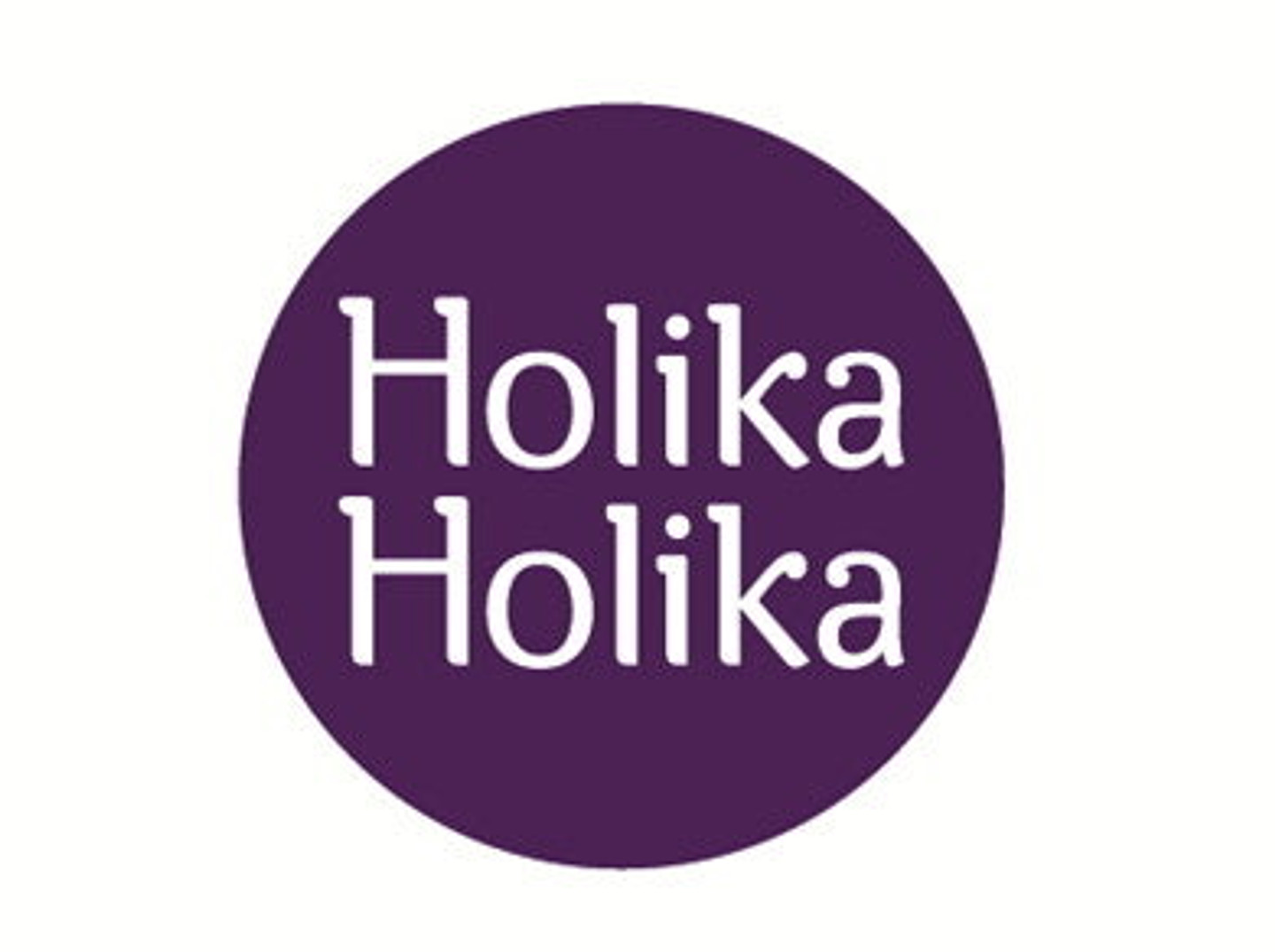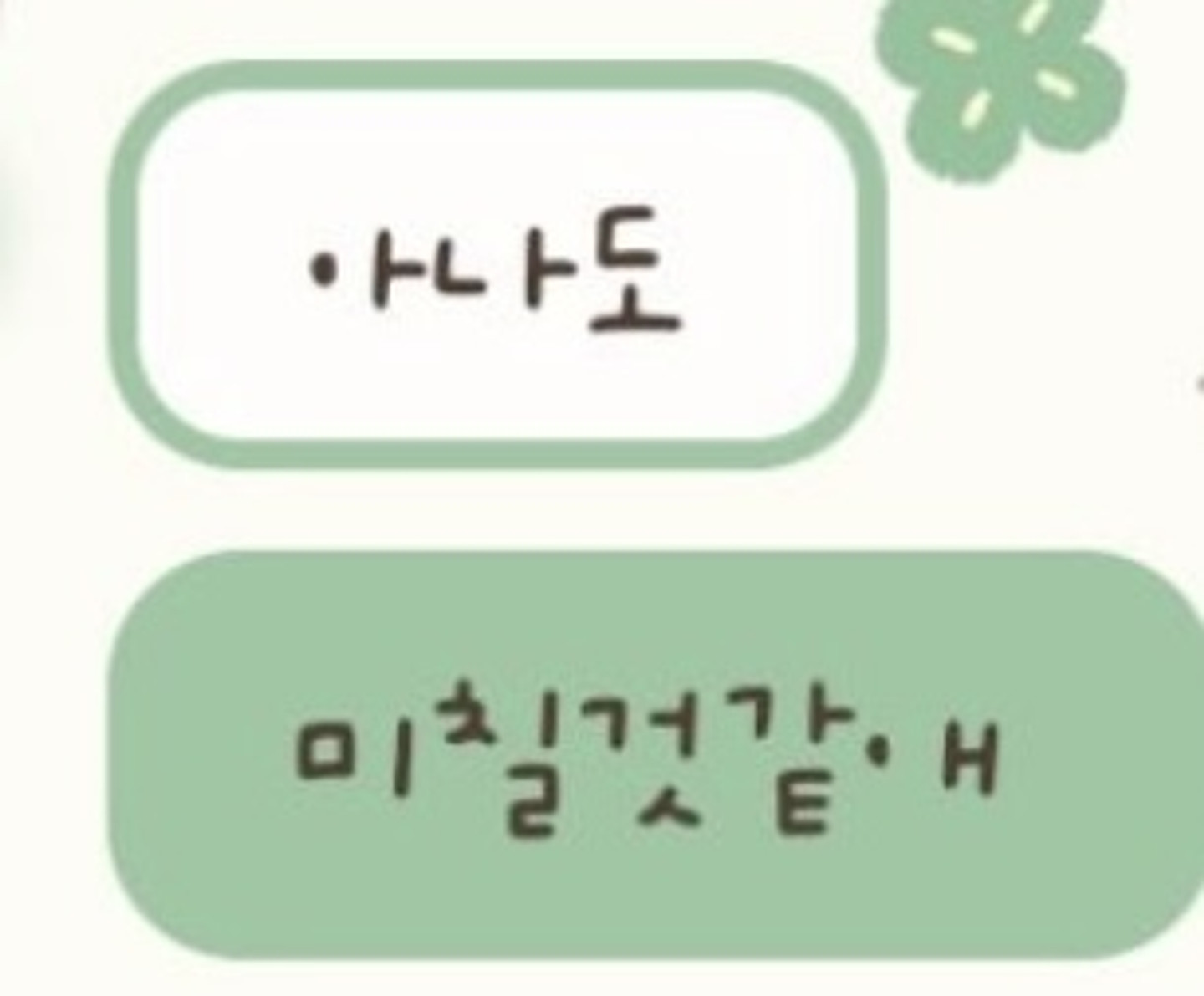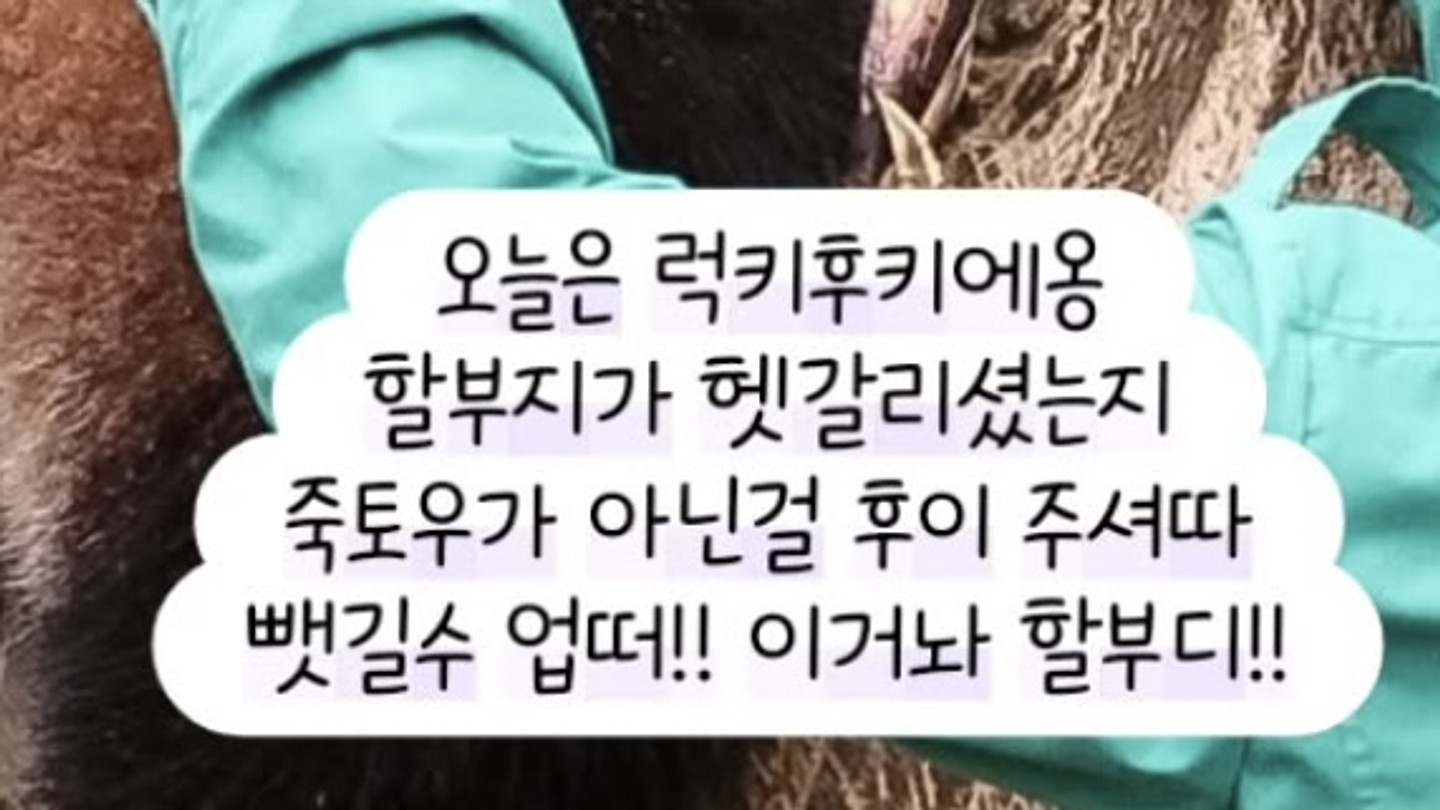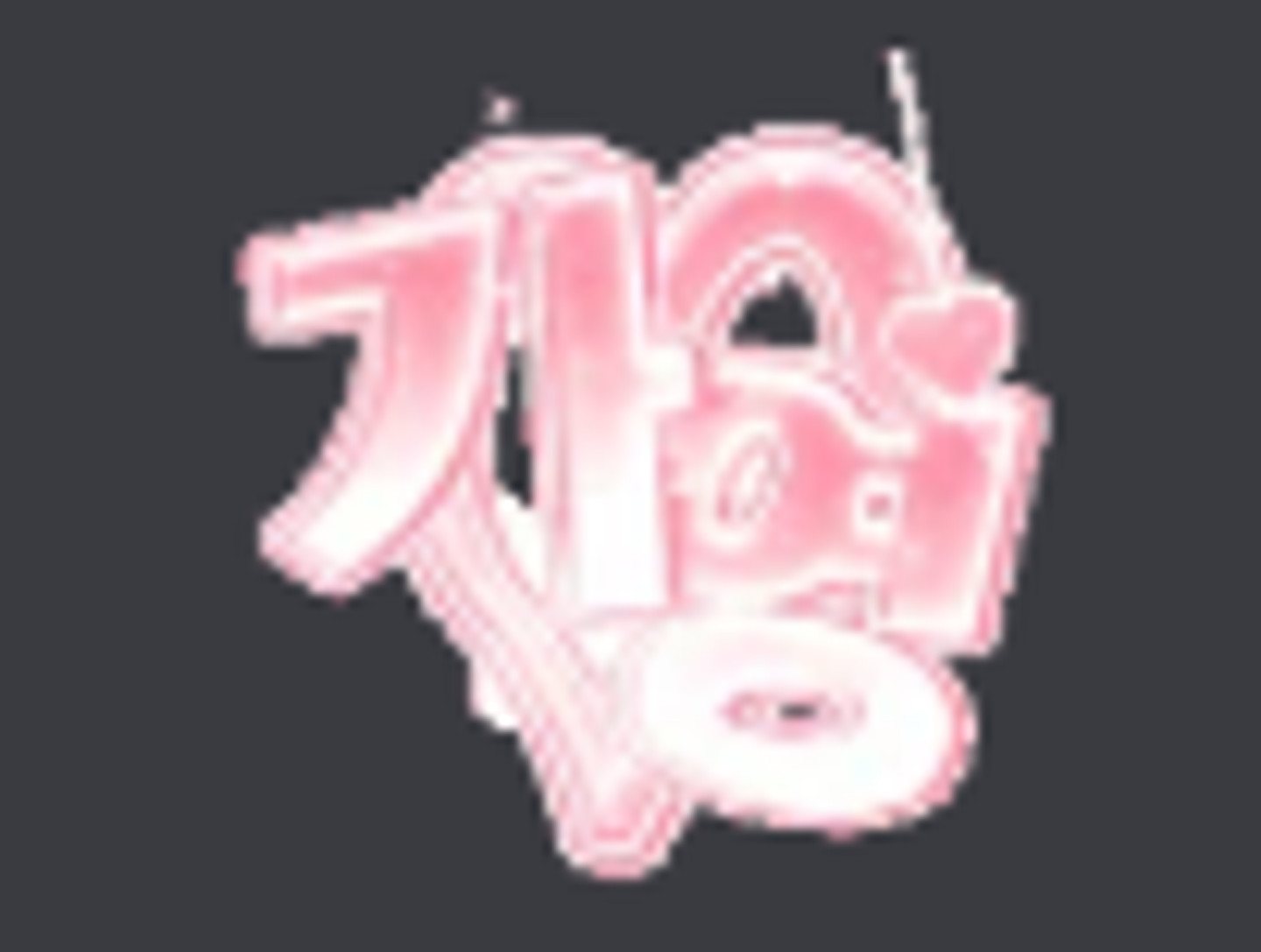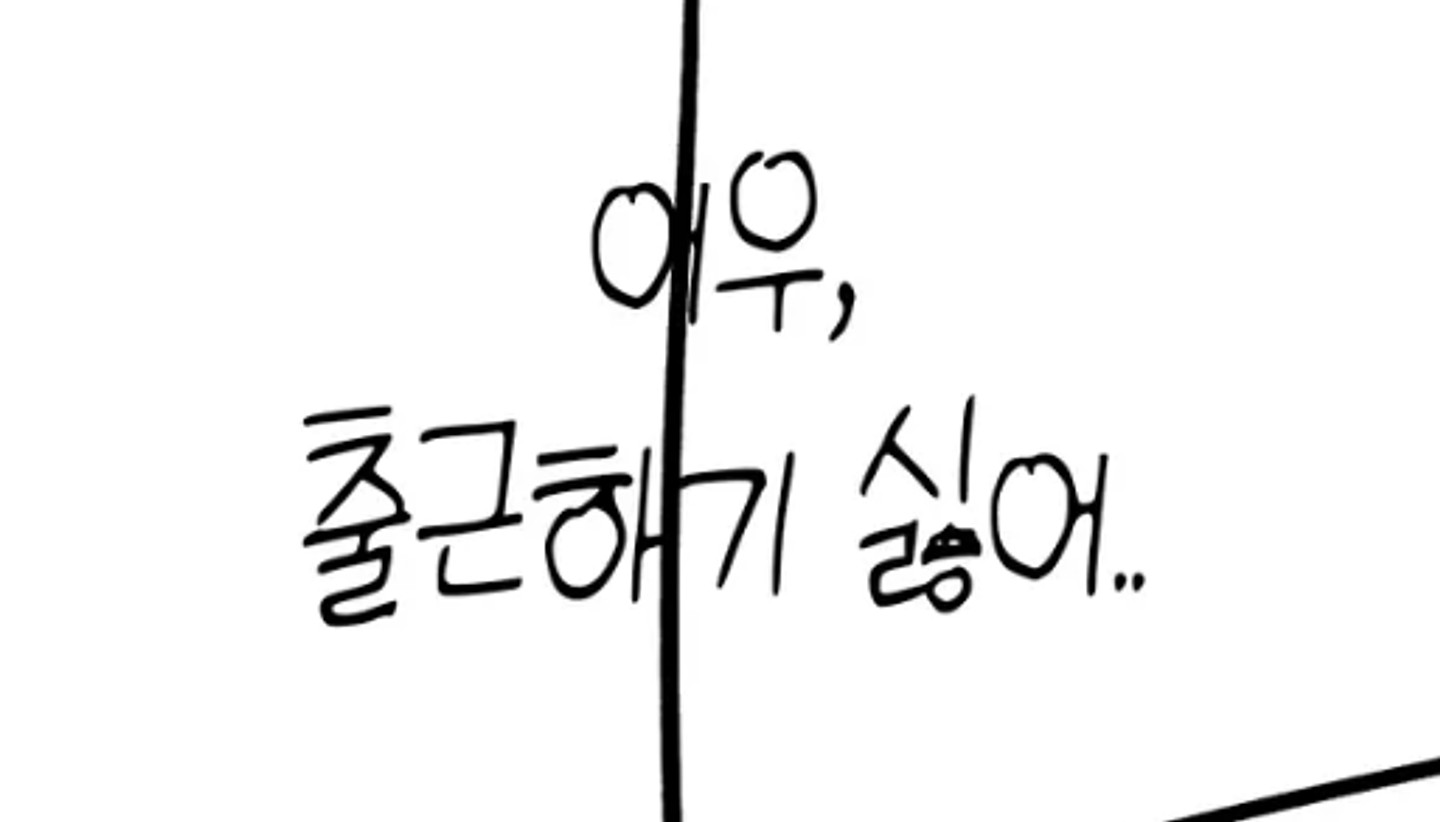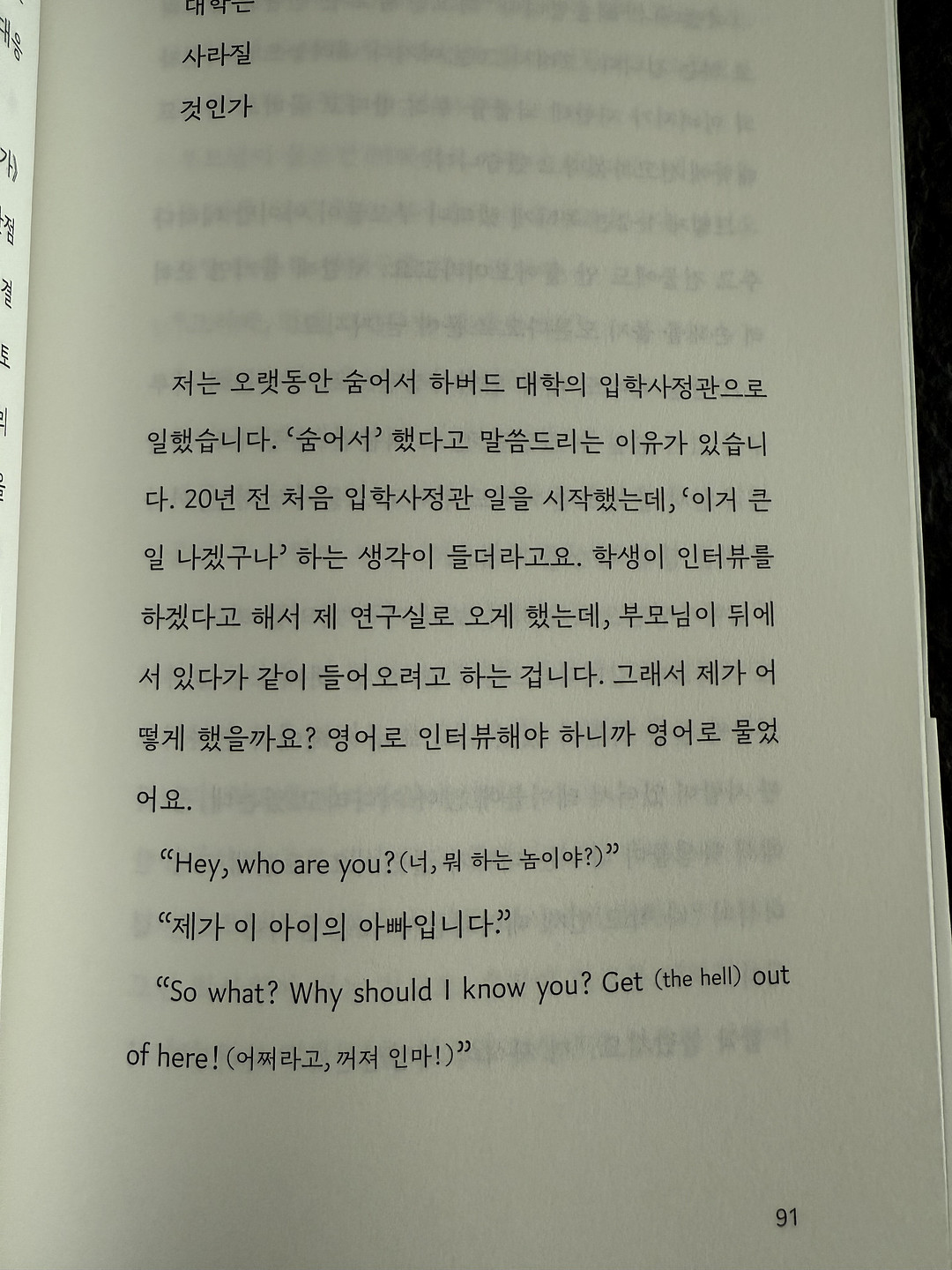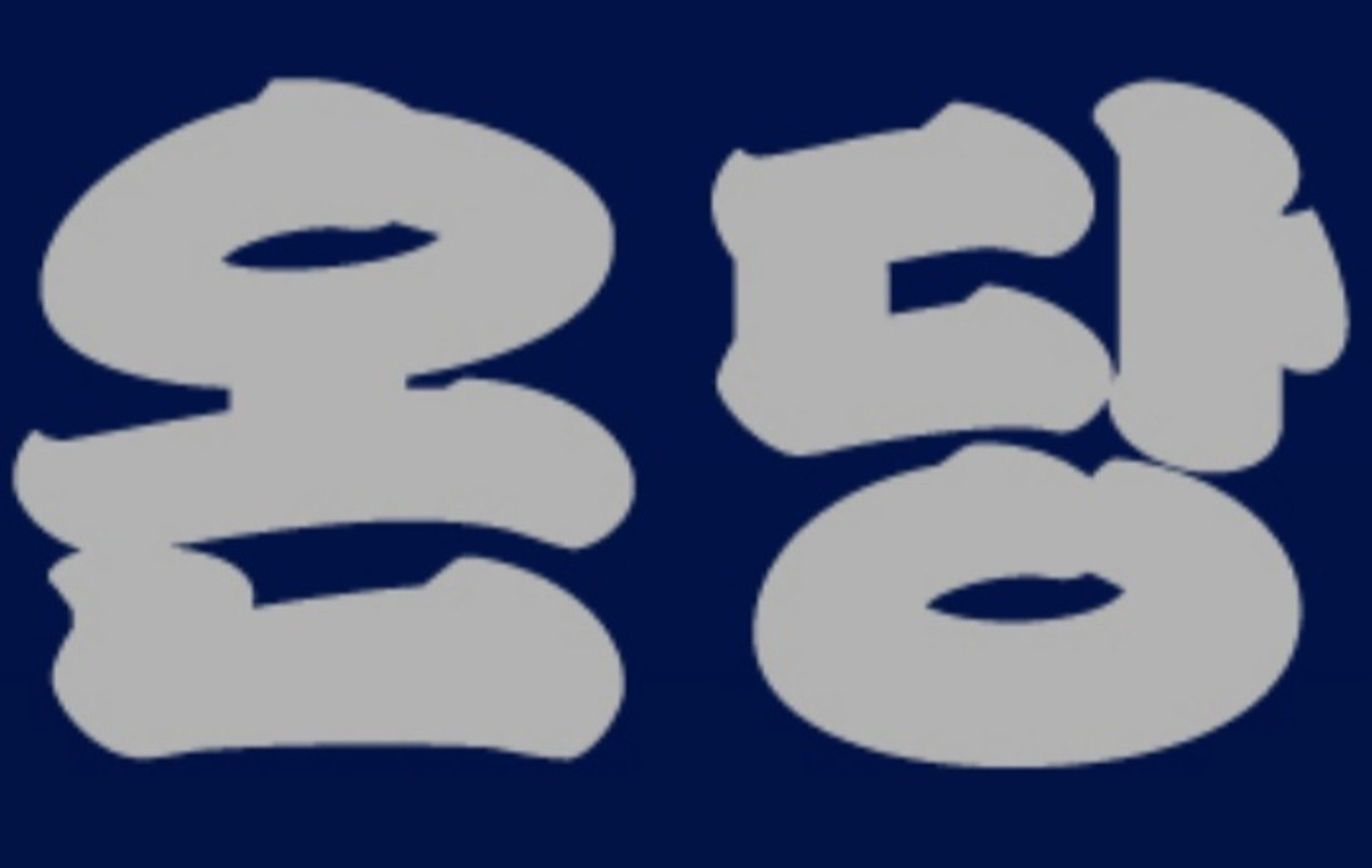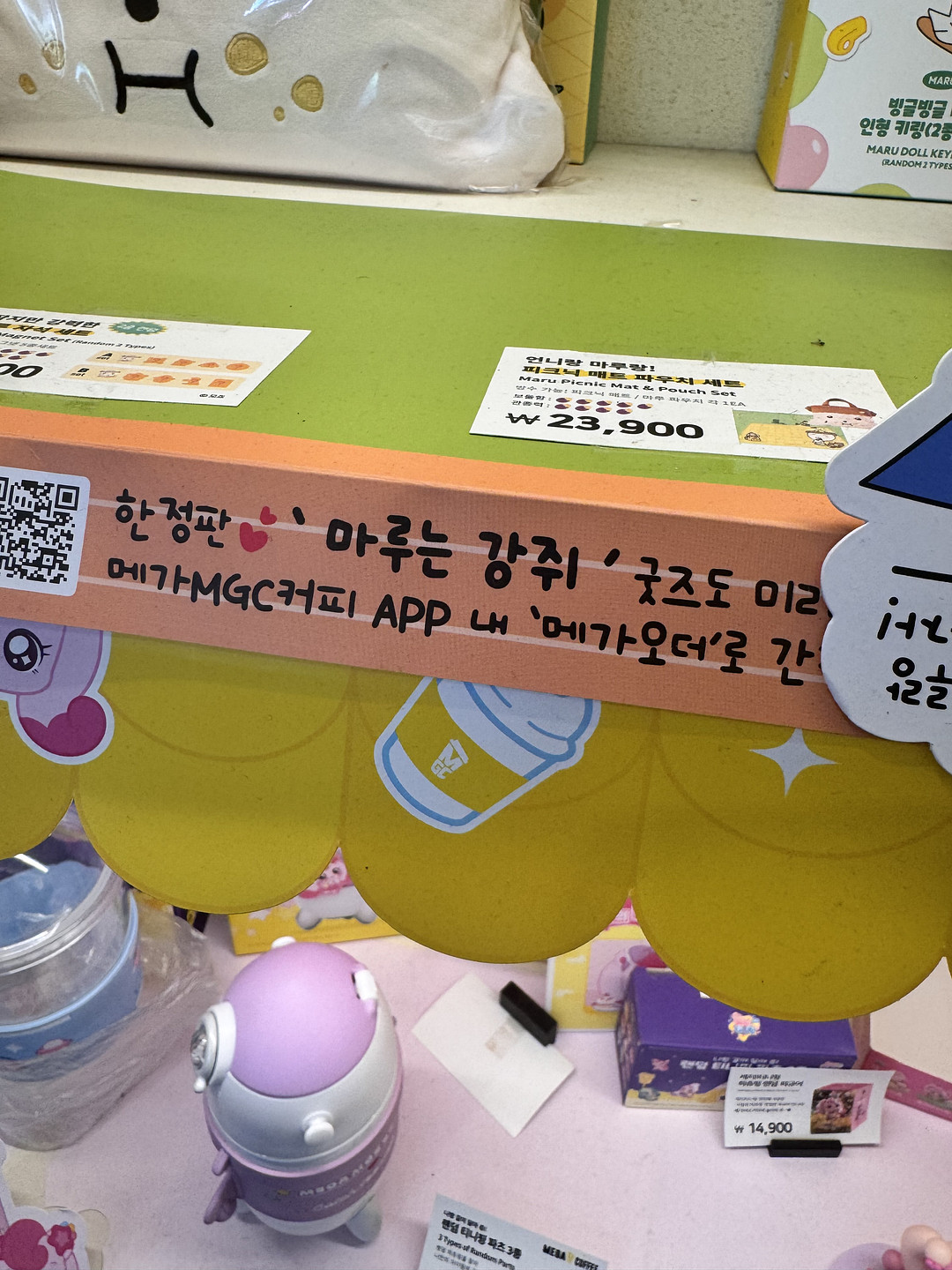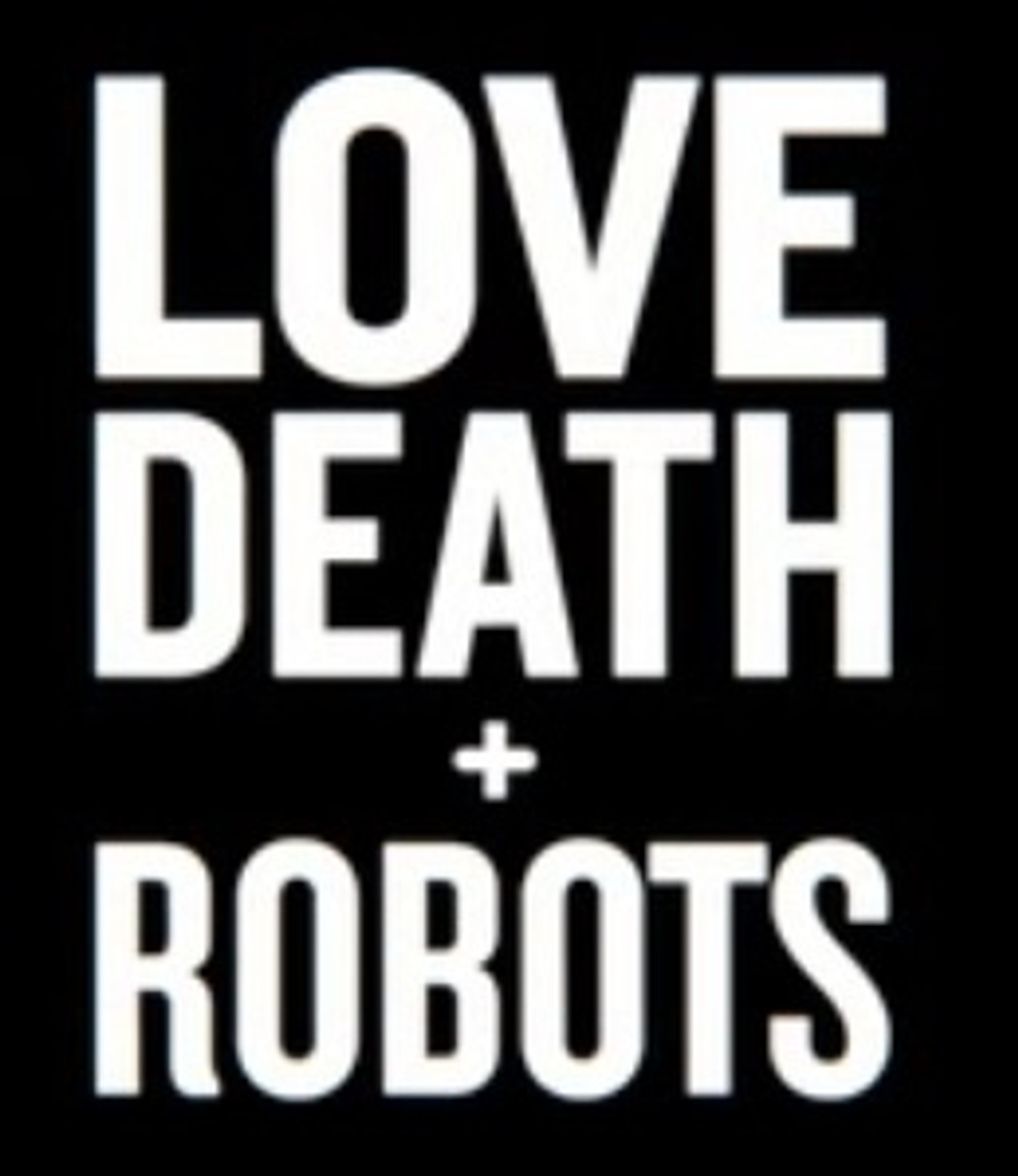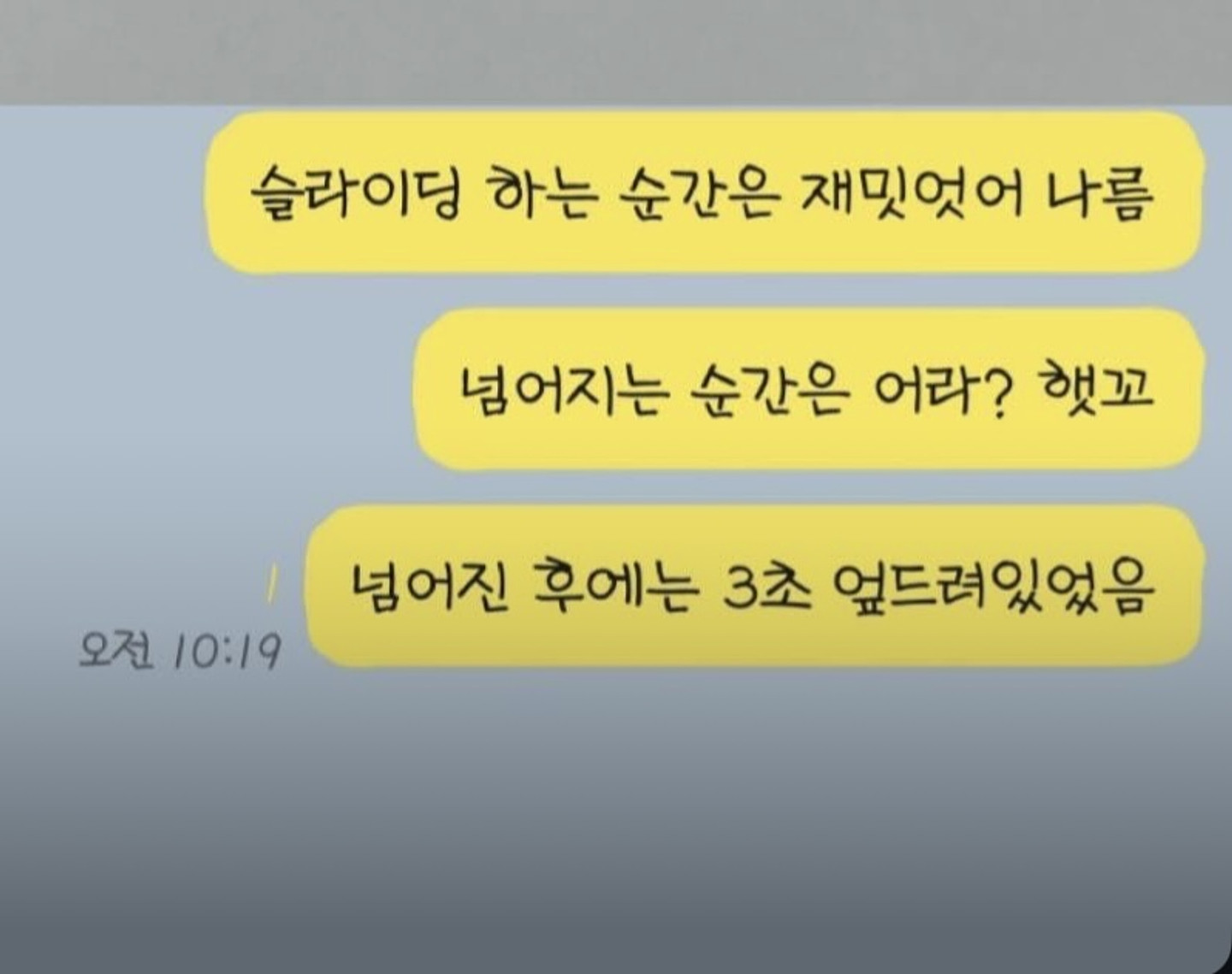
깔끔한 돋움체 스타일인데 노토산스 프리텐다드 다 비슷비슷해서... 정확하게 모르겠네요ㅠ
이거 폰트 찾고싶어요!! ㅜㅠ
기울임 적용된 상태인 걸로 보이는데 혹시 무슨 폰트인지 아시는 분 계실까요?ㅠㅠㅠ
ㅠㅠㅠㅠㅠ폰트 찾는거 도와주세용
폰트아시는분 ㅠㅠㅠㅠㅠㅠ 진짜 못찾겟어용
고수님 찾아주세요 ㅠㅠㅠㅠㅠ
무슨 서체 일까요?
맛살구글체는 무슨체인가요?
무슨 서체인지 아시는 분?
비슷하게 생긴 폰트가 있다면 알려주세요...!!
무슨 폰트일까요!
이 폰트 알려주세요
갓삶아낸돼지고기가나오는시간 이거 무슨 폰트인가요ㅠ?
이 폰트 너무너무 알고 싶어요 ㅠㅠ
무슨폰트인가요? 위아래 같은건 아닌것같은데
무슨 font 일까요 pretendard도 아니고 noto sans도 아니고 roboto nunito는 절대 아니고 montserrat도 아니여요...
무슨폰트죠?
투썸플레이스 문구인데 폰트 뭔지 궁금해욘
무슨폰트인가요 ㅠㅠ?
이거 무슨 폰트인지 아시는 분~
Round 폰트 알려줘
이 폰트 알려주세요 ㅠㅠ
폰트 정보 아시는분 계시나요?
이폰트 알려주세요
안녕하세요 이 폰트 이름 뭔지 알 수 있을까요?
폰트 뭘까요? ㅜ
폰트명 알려주세요
고수님들 이 글씨 폰트 어떤건지 알 수 있을까요....??!!!!!
순바탕제나 마포금빛나루와 비슷한데 이 폰트가 뭔지 꼭 알고 싶어요
이 글씨체 뭔가요??
이거 무슨 폰트 일까요 ㅜㅜ????
혹시 이 폰트 무슨 폰트인지 알 수 있을까요 ?!
상단과 하단에 쓰인 영문폰트를 찾고있는데 모르겠어요. 아시는분 계실까요?
이 글자체 뭘까요?
이 자막 폰트 알려주세요~~
이거 무슨 폰트인가요? ㅠㅠ
이거 타이틀 무슨폰트인가요??
디자인인지 폰트인지 모르겟는데, 폰트면 사용하고 싶어서요..!
저거 무슨 폰트인가요?
이거 영문폰트 어떤거 일까요 ㅠㅠ
폰트 알려주세요ㅜ
이 폰트 뭔지 너무 궁금해요,,굴림체같은데 나눔굴림은 아닌거같아서요ㅠㅠ
혹시 이 폰드 아시는분 계실까요? 찾아봤으나 헤드라인, 정헤드는 아니였습니다.... 폰트 알고싶습니다!
끝이 가운데로 모이는 폰트인거 같은데 보통 바깥으로 빠져서 무슨 폰트인지 알고 싶어요..
대한방사선사협회 경상북도회 폰트를 알고 싶어서 올립니다. 많이 본건데 아무리 찾아도 안나오네요 부탁드립니다.
'5월 5일 어린이날, 이날만을 기다렸다!' 이 부분 폰트 아시는 분 계실까요 ㅠㅠ?
고수님들 이건 무슨 폰트인가요?
폰트 알 수 있을까요ㅠㅠ
심야괴담회에서 본 폰트인데 손글씨일까요? 폰트라면 어떤폰트인지 아시는분?
폰트명 알려주세요ㅜ
글씨체 뭔가요? 무료일까요 ㅠㅠ